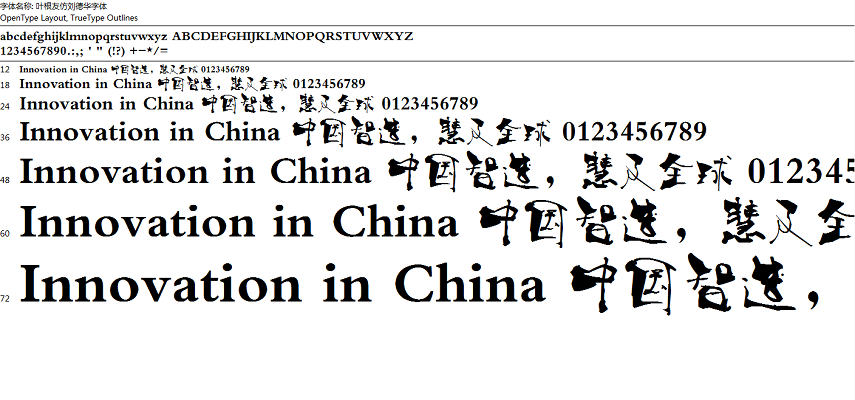
葉根友仿劉德華字體是一款劉德華先生字體的仿版,字體表現(xiàn)十分自然,又極顯逼真,如果有劉德華先生的粉絲,一定不要錯(cuò)過(guò)這款字體哦,趕快來(lái)綠色資源網(wǎng)下載體驗(yàn)吧!
劉德華字體葉根友仿版是由中國(guó)書法奇人葉根友先生模仿香港明星劉德華先生的手跡書寫,字體清晰自然,實(shí)用性強(qiáng),是書寫信件,BLOG等個(gè)性化字體的一不錯(cuò)的選擇.